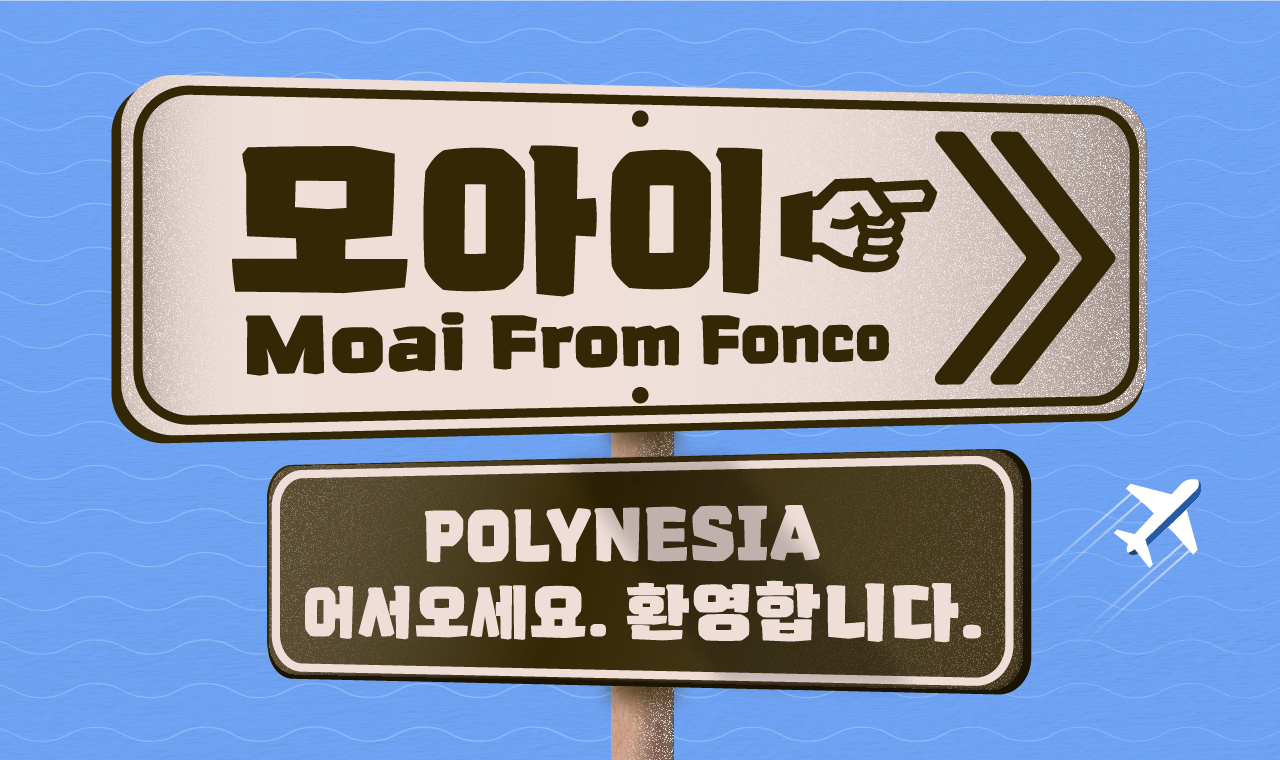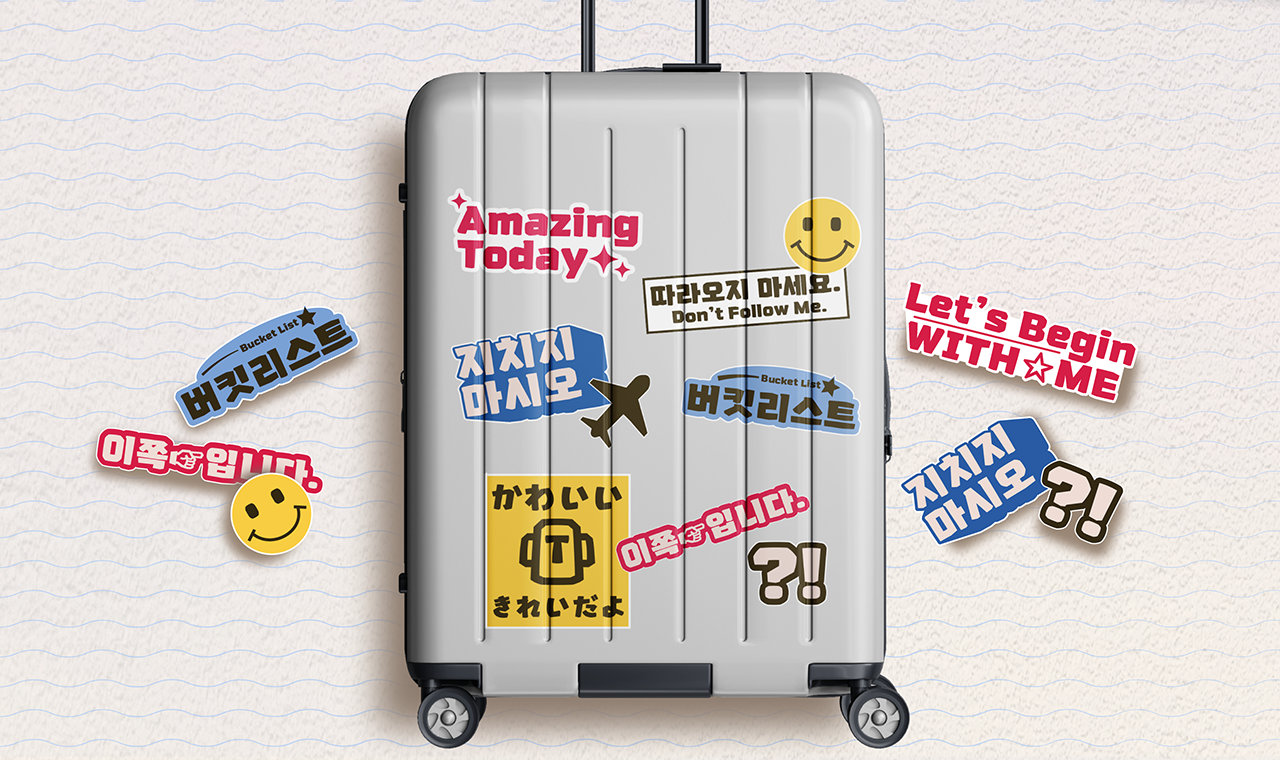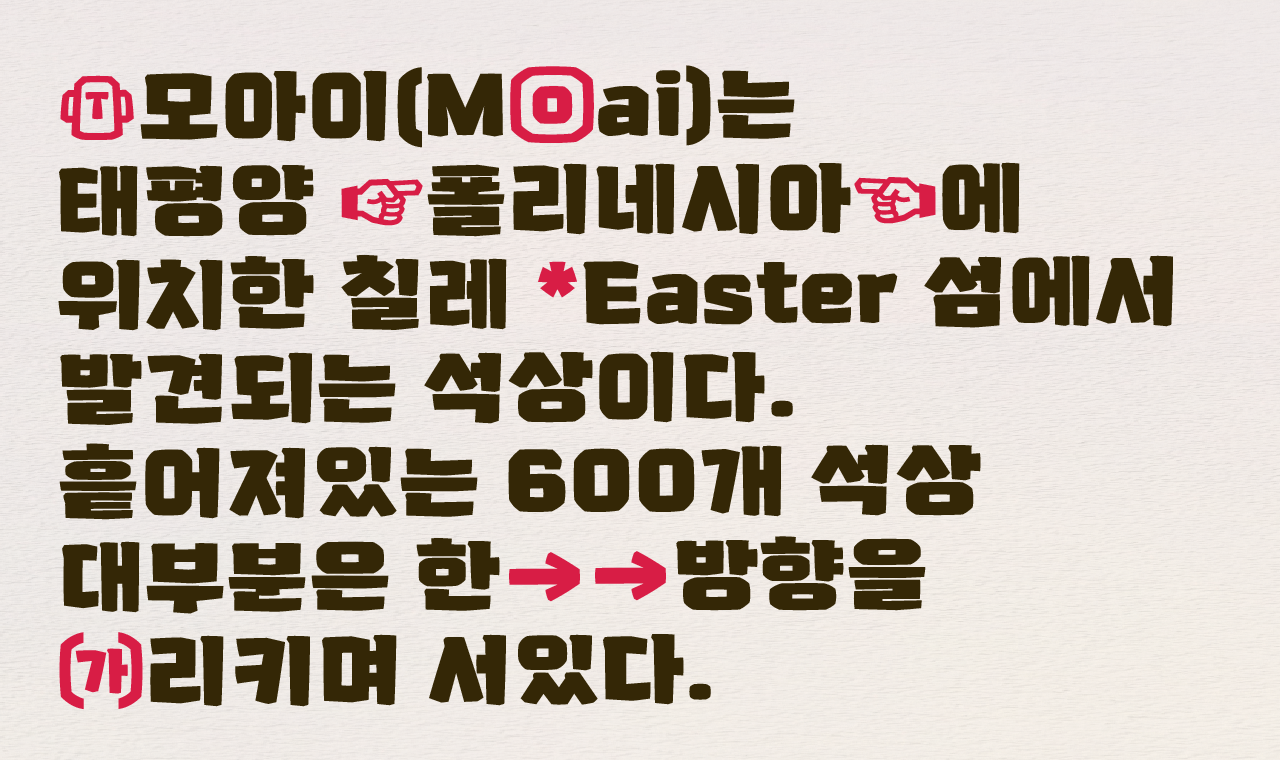
모아이는 돌을 깎은 듯한 형태의 제목용 서체입니다. 각지고 직선적인 자소의 형태가 특징이며, 꽉 찬 모듈로 아이가 돌을 쌓아 올린 듯한 귀여운 인상을 줍니다. Black의 굵기와 큼직큼직한 자소로 영상 썸네일, 포스터 제목 등 강조가 필요한 곳에 사용하는 것을 추천합니다. 두껍고 어두운 이미지와 트로피컬의 시원함, 화사함을 모두 담아 서체 이름을 '모아이(Moai)'라고 정하게 되었습니다.